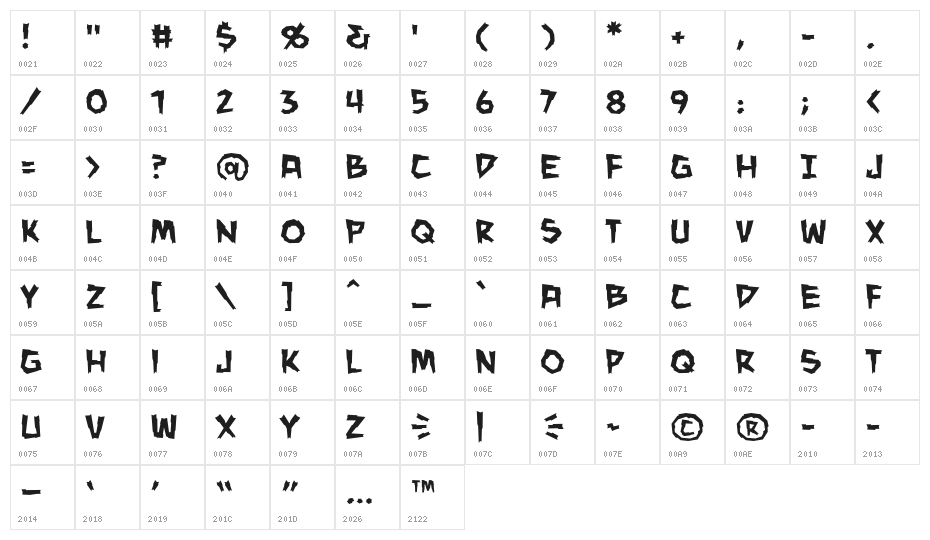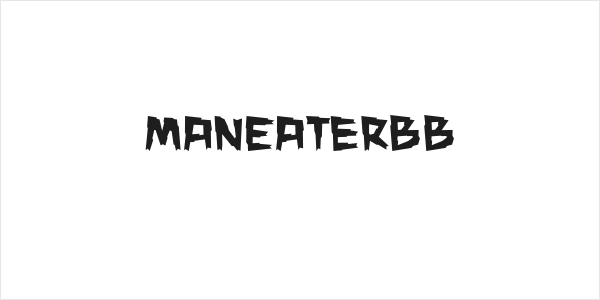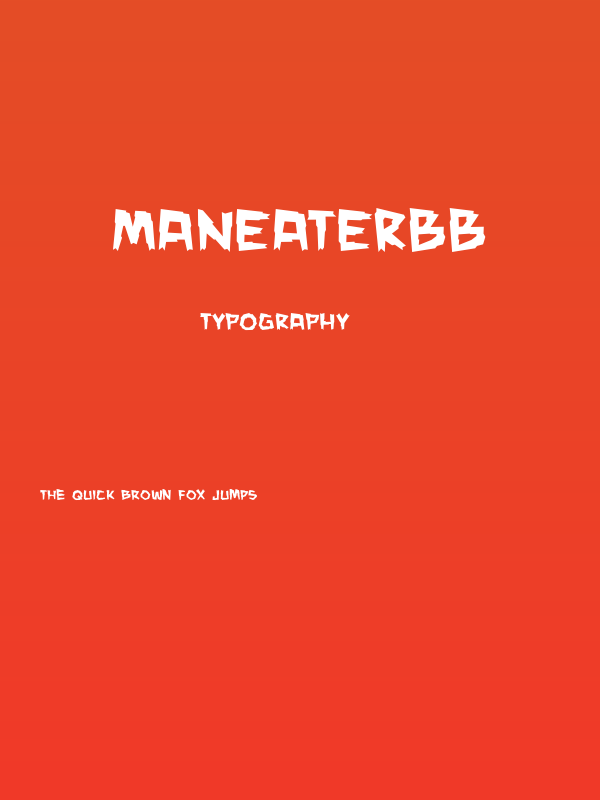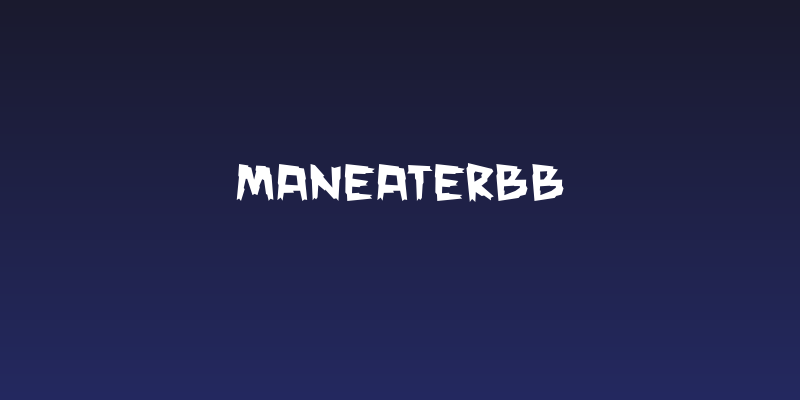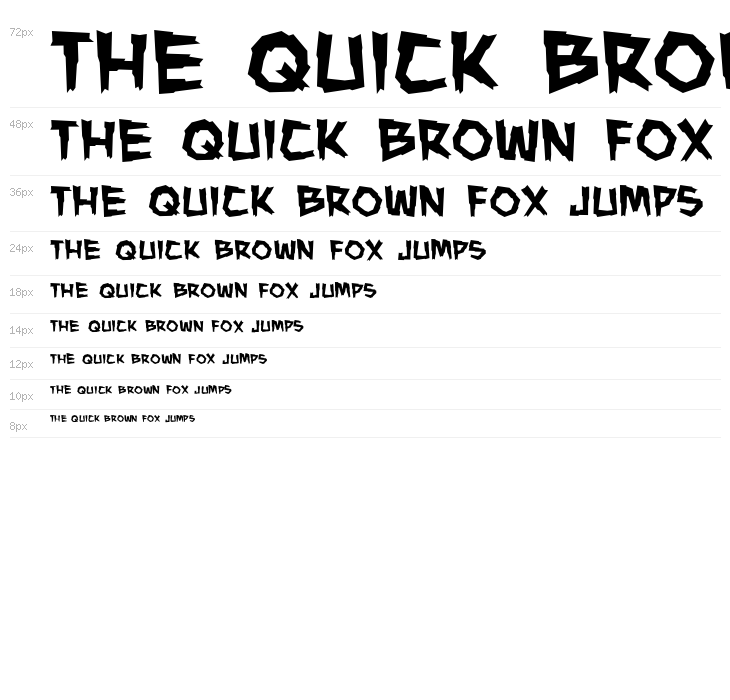
ManEaterBB Font
| Stile generale | Edgy, Dramatic |
| Caso d'uso | Headlines, Posters, Logos |
| Progetti proposti | Perfect for horror-themed designs, edgy posters, album covers, or video game graphics. |